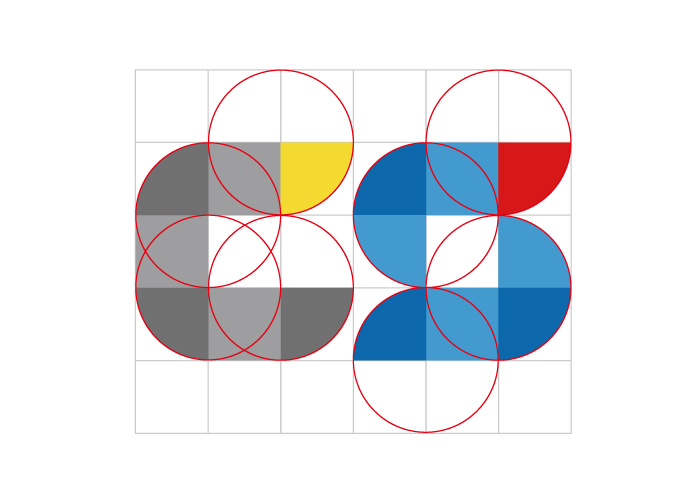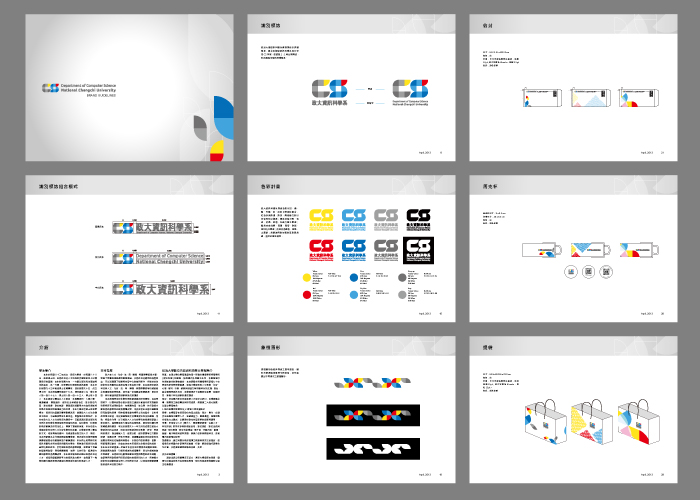
政治大學資訊科學系
本創作利用拼圖拼貼概念來呈現,製作出傳統標誌與動態標誌規範,並設計出未來可更活躍運用的三組視覺形象。
設計方法與理念:
政治大學資訊科學系識別標誌以拼圖概念,組合出縮寫資訊科學系英文字母CS 字樣,並透過1:1 等比例構成,字母弧形組合方式透過相等之四個圓形組成,在視覺上具有平衡的美學概念。
動態商標概念一:以片頭式動態呈現,概念來自於貪食蛇形態,動態變化時的形態,亦可作為應用項目之延伸。動態商標概念二:以限定範圍內,使用者可自由編排組合,以肌理作為動態變化。動態商標概念三:以限定區塊的色彩,使用者可依範圍內選擇弧形或方形以及旋轉角度作為客製化變化方式。動態商標概念四:每個學生入學時可領 driver license,畢業時則可有自己的 license plate(如附件),車牌上用5個數字 + 兩個自訂字母。象徵畢業後可開上 information highway大展鴻圖。
傳統標誌規範、動態商標設計